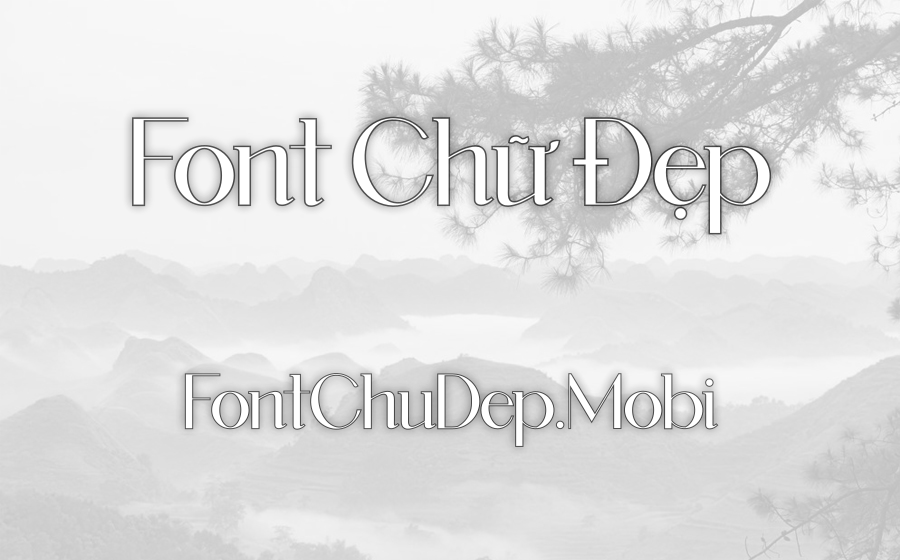
Font VL Amelaryas Việt Hóa
VL Amelaryas
Nói về VL-Amelaryas, đây thực sự là một phông chữ serif tạo nên sự ấn tượng mạnh mẽ bằng phong cách sang trọng và đầy lôi cuốn. Được sáng tạo bởi Hishand Studio, VL-Amelaryas gây ấn tượng với các đường nét nhẹ nhàng và chân chữ tinh tế đến từng chi tiết, mang lại vẻ đẹp đẳng cấp và lịch lãm cho mọi thiết kế.
Sự thanh lịch và rõ nét trong thiết kế giúp VL-Amelaryas trở thành lựa chọn lý tưởng cho nhiều ứng dụng khác nhau. Dù là tiêu đề, văn bản dài, thiết kế logo hay các ấn phẩm in ấn, phông chữ này đều tỏa sáng với phong cách riêng biệt. Đặc biệt, trong lĩnh vực tổ chức sự kiện, VL-Amelaryas góp phần tạo nên không khí trang trọng cho các hội nghị, lễ kỷ niệm và sự kiện văn hóa. Ngoài ra, phông chữ này còn phù hợp với các ngành nghề như xuất bản, giáo dục và truyền thông, nơi yêu cầu cao về tính thẩm mỹ và sự chuyên nghiệp.